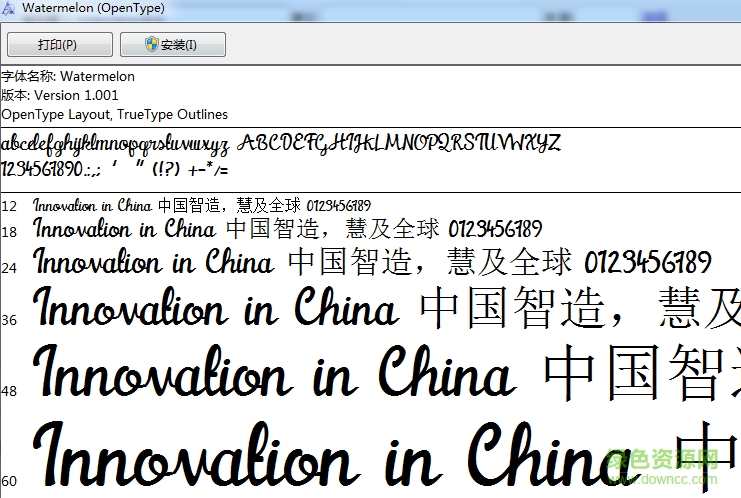
Watermelon字體是英文字體庫(kù)中的個(gè)性字體,字體的線條非常飄逸,讓用戶能夠輕松彰顯自己的個(gè)性,有喜歡的朋友就來(lái)綠色資源網(wǎng)下載使用吧!
Watermelon字體是一款個(gè)性英文字體,該字體的字型瀟灑,給人一種過(guò)目難忘的感覺(jué),有需要的朋友就趕快來(lái)綠色資源網(wǎng)下載吧!